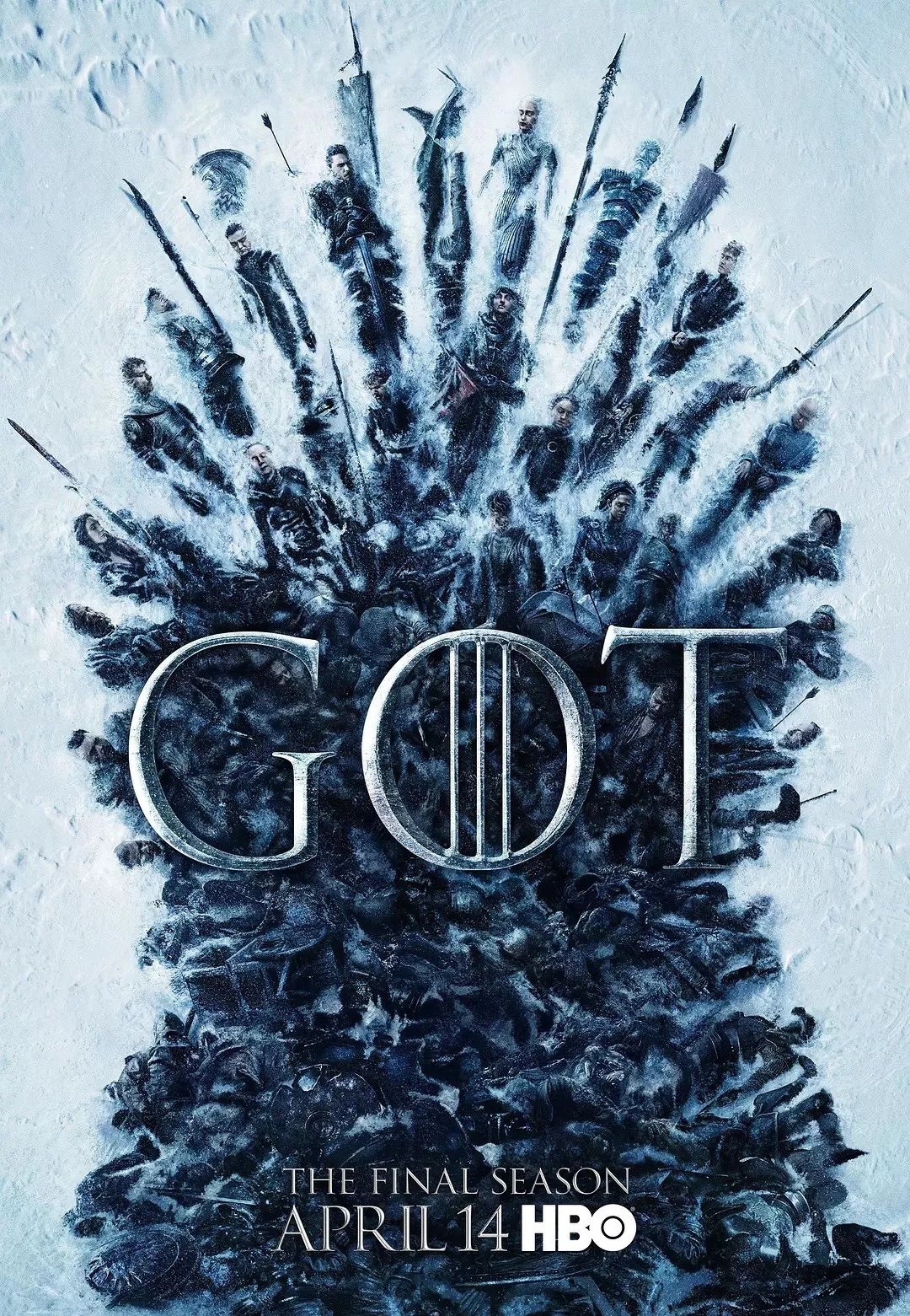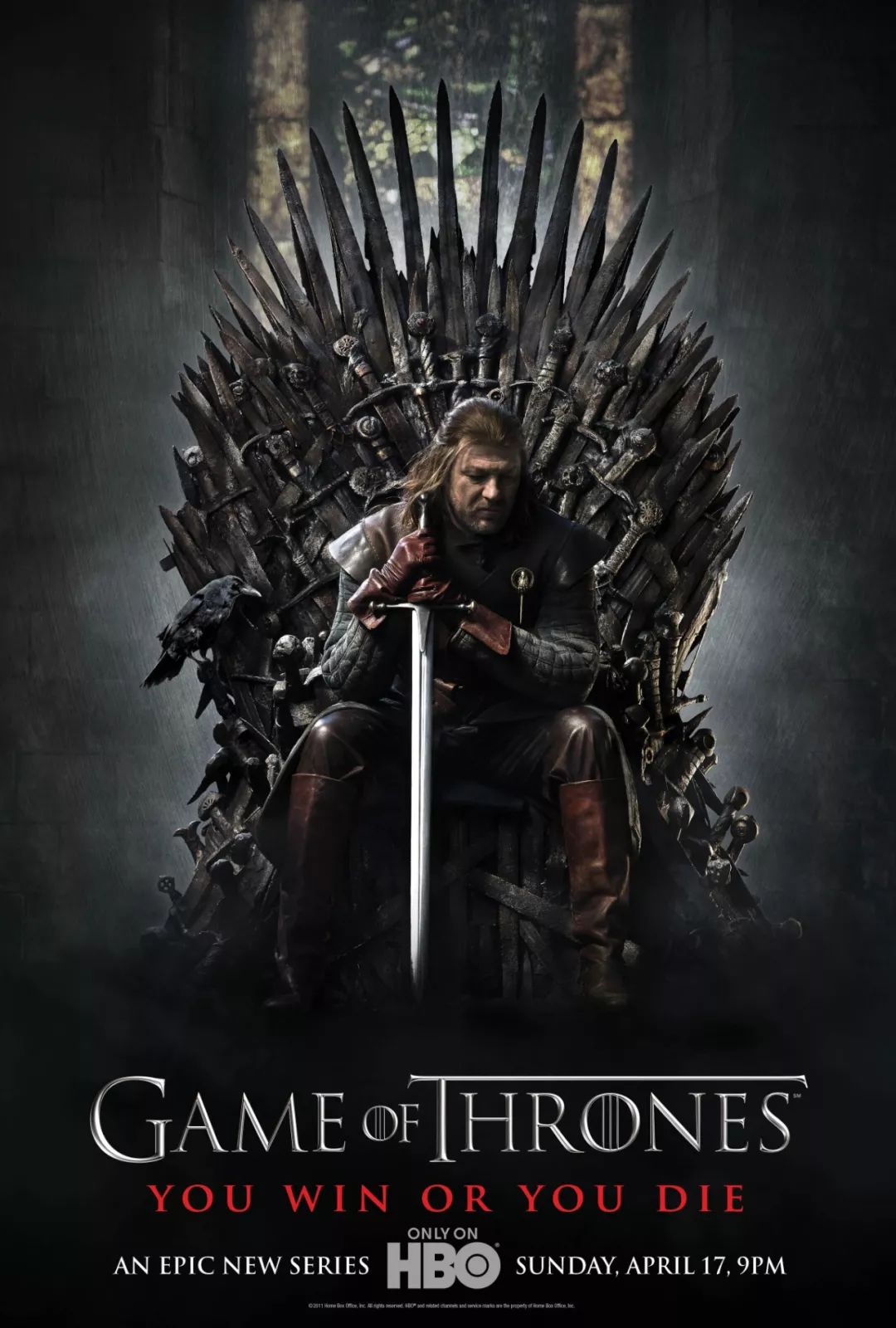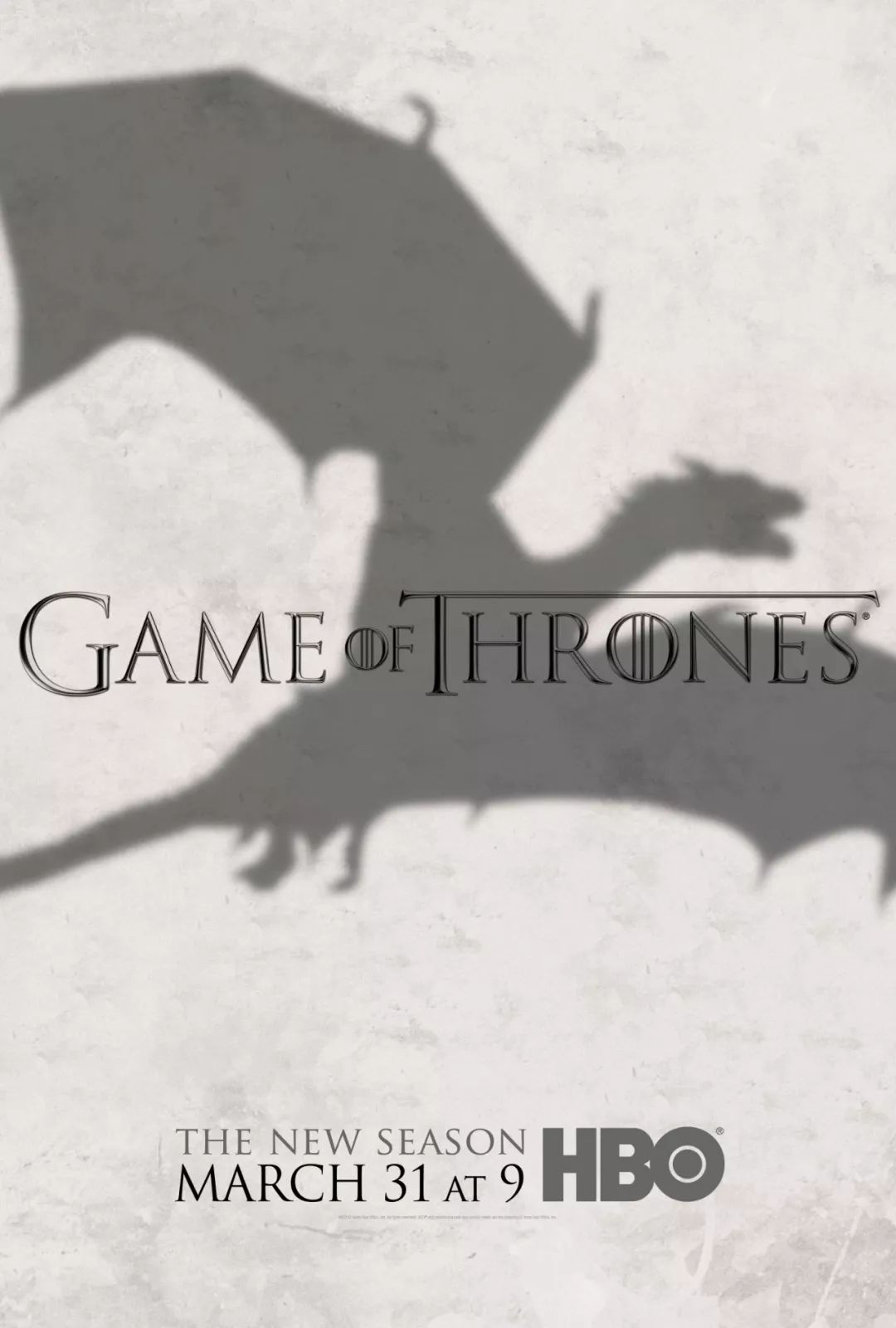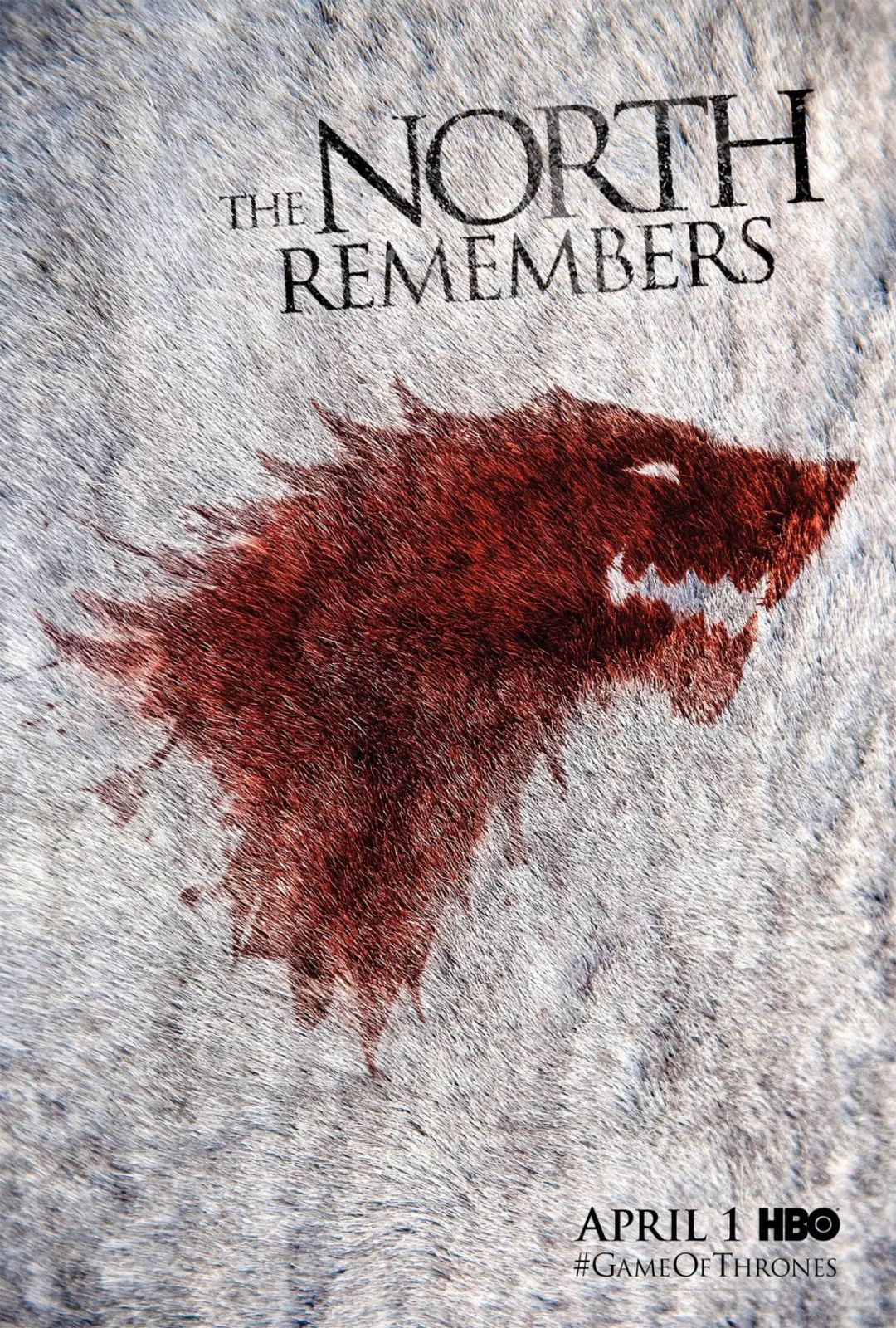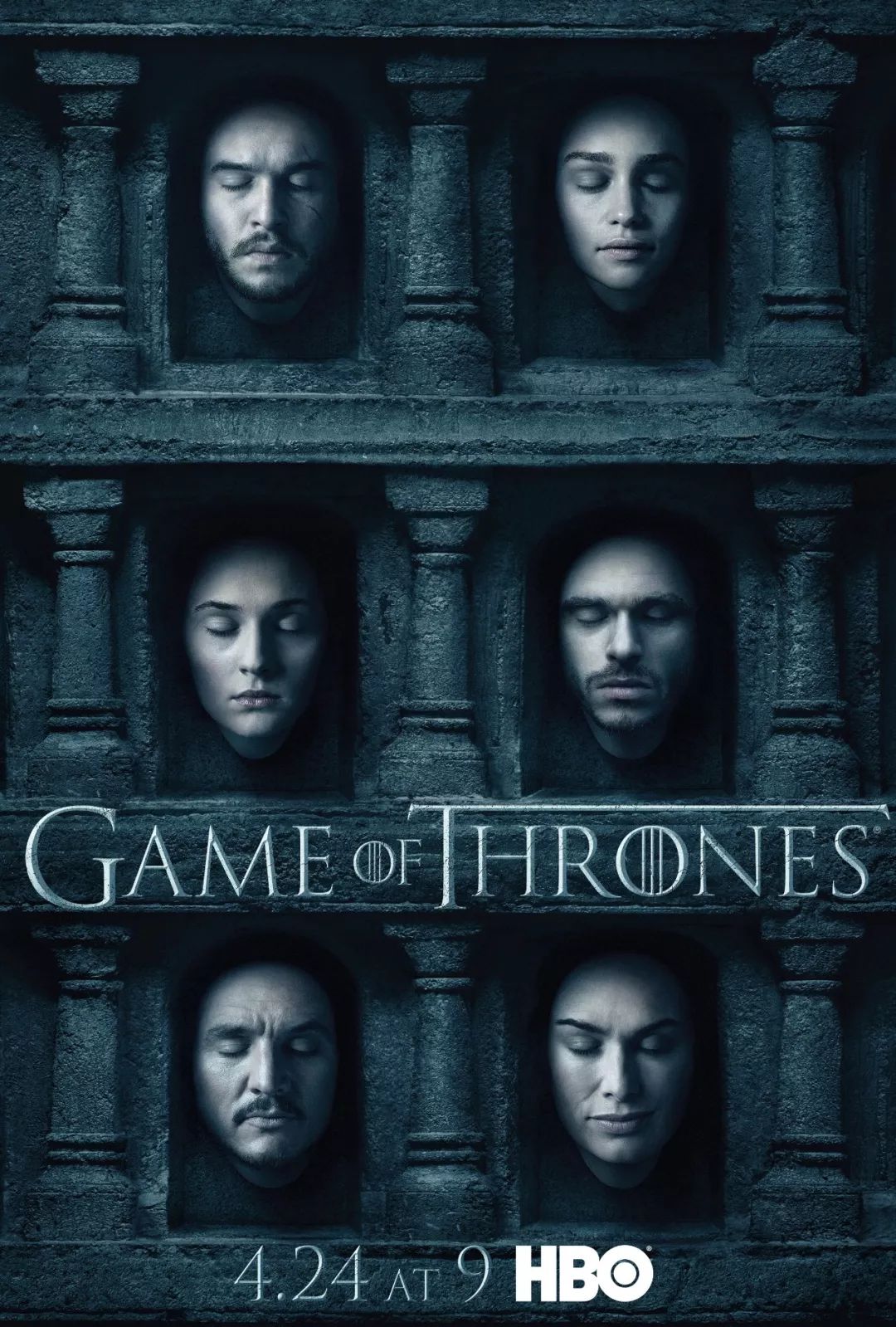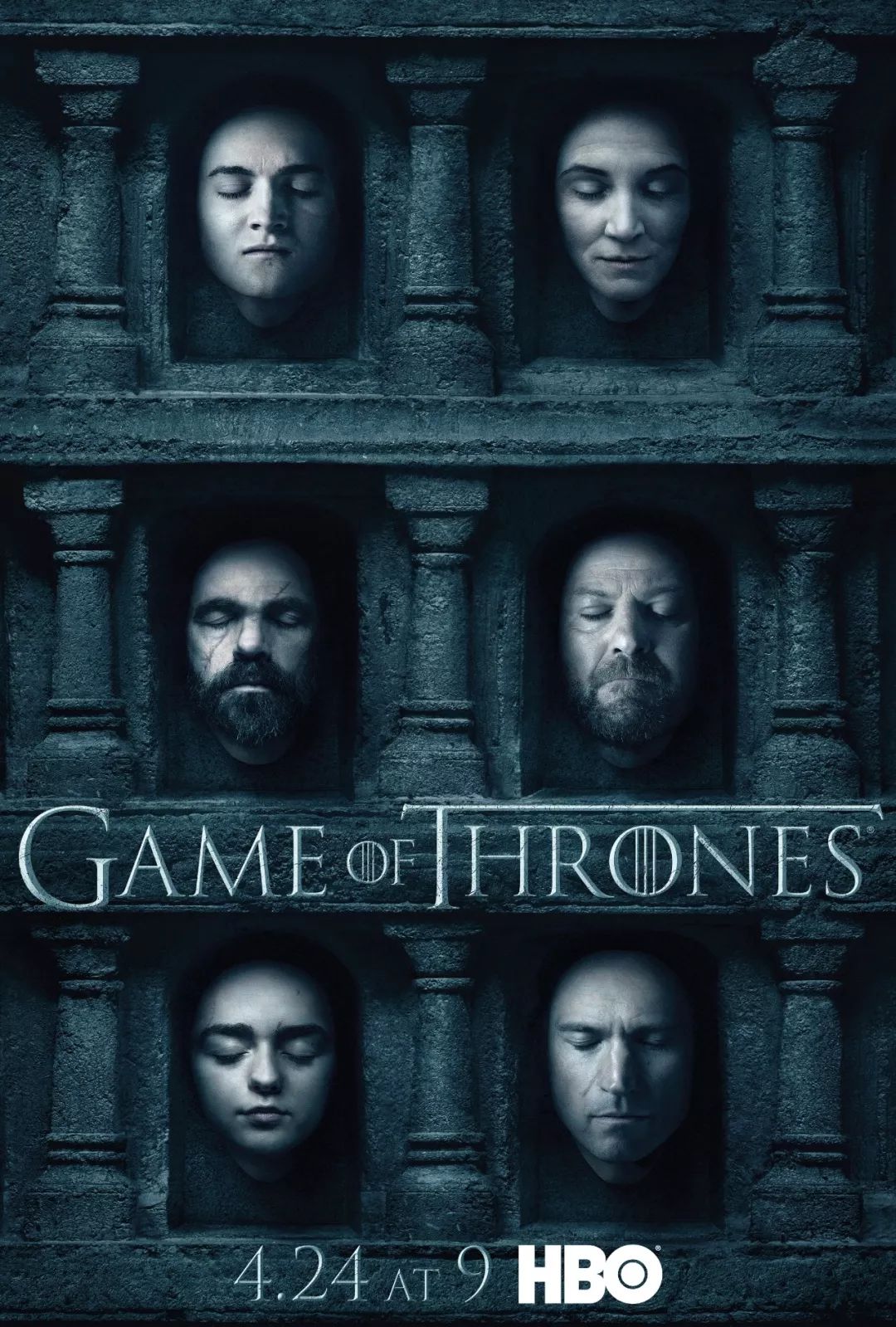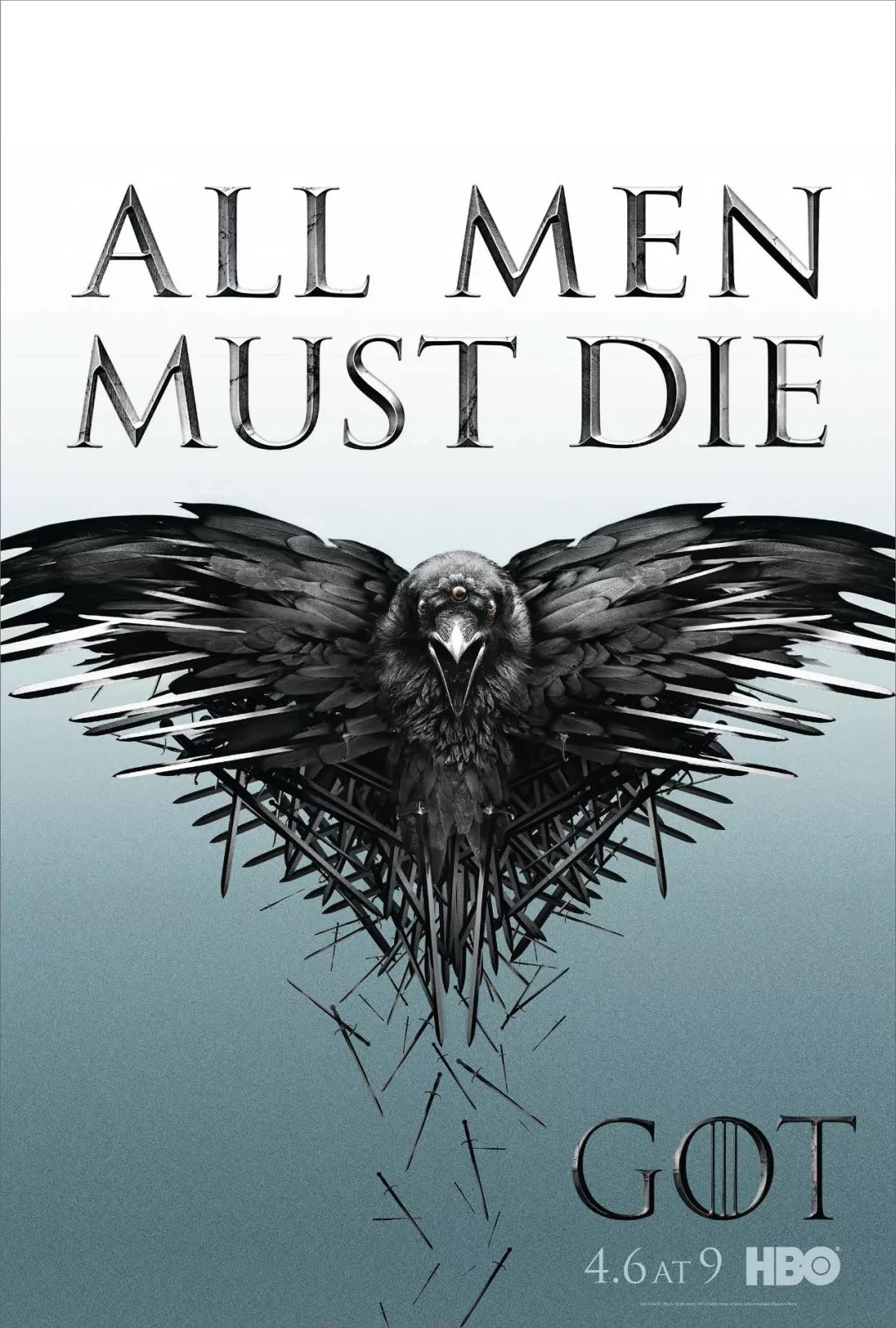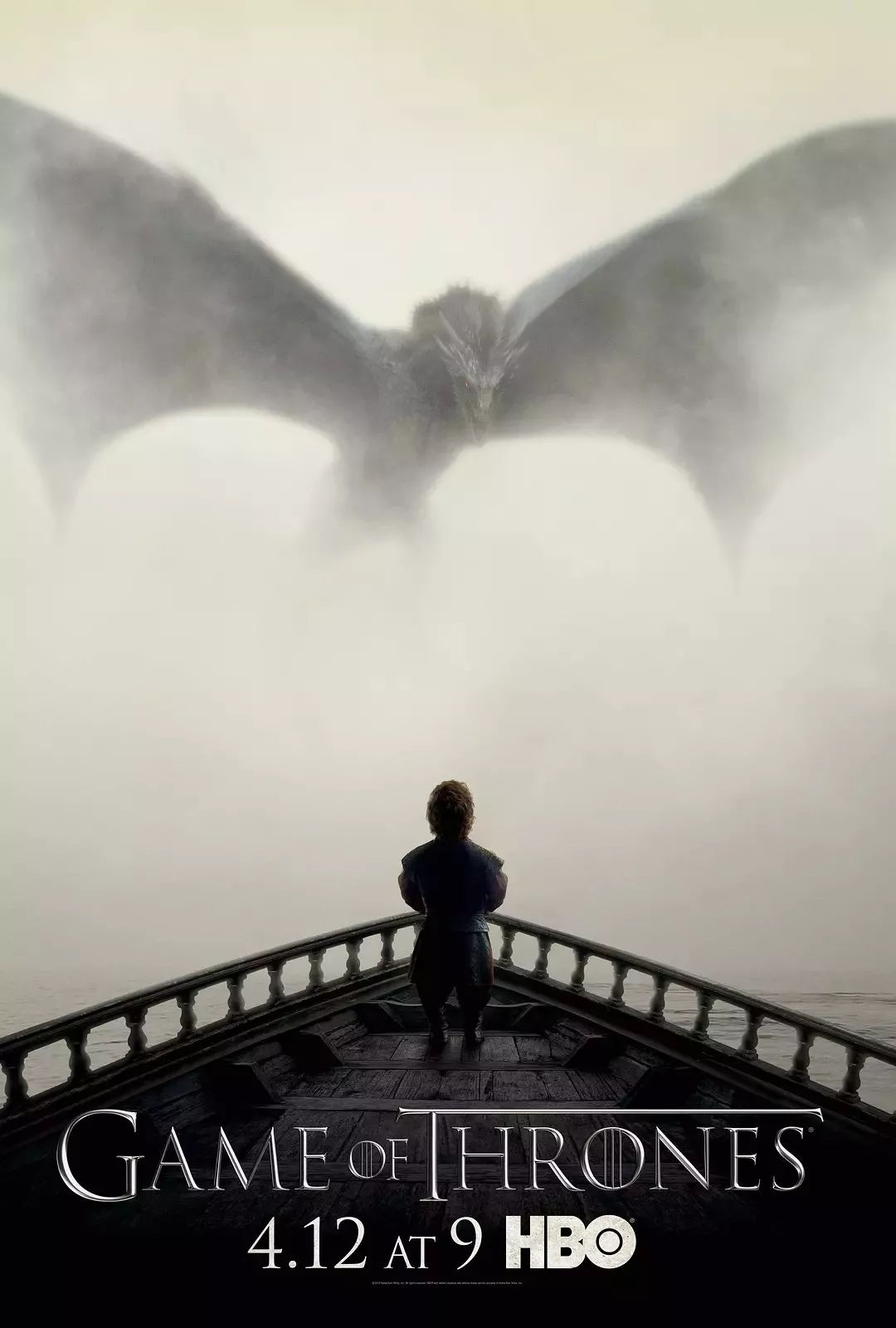
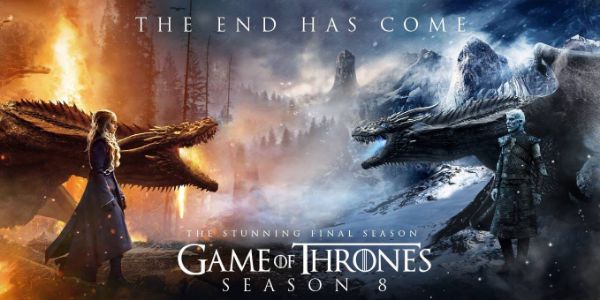
《权力的游戏》才是真正的996
想必大家今天都无心工作,等着追《权利的游戏》第八季吧,作为一个美剧盲的我,也被朋友圈各种“广告”着~
不关注都不行了,可是当我想补课时,却发现进入了一个大坑,这部从2011开播以来的剧,堪称人类的命运史,也就是不断地死亡,不断地权利更替……
看看第八季的海报就知道了~
有点渗人吧,但它的灵感来源却是我们再熟悉不过的了。
很多铁粉试图辨识爱豆的“尸体”,找到故事的结局,不过预告片也可以~
龙妈、夜王、雪诺、小恶魔、二丫、弑君者等21位重要角色霸气亮相,虽然只有短短六集,但投资就高达一个亿(电视剧史上最高),所以即使每周一集,也甘心会员充好(520完结,也是醉了)。
但对于我这种美剧没看过,《权力的游戏》更没听过的小白,有必要三分钟恶补一下。
嗯,还是一头雾水,无奈人物太多,支线太杂,智商有点不够,那就先从海报看起吧~
第一季的海报比较经典,感觉第八季像是跟它呼应一样,只是刚开始挂一个,后面全挂了。
其它角色海报,也是同一个视角,一字排开,但文字排得乱~
最喜欢这张,乌鸦舔血,这才是权利的意境。
第二季很复古,突出了金色字体,但有点《饥饿游戏》的感觉。
预告海报里倒是有几张惊艳之作~
这张真是美出了小龙女的感觉~
第三季有点中规中矩,看不出霸气,只嗅到了一丝诡异~
又是角色海报占了上风,一半是海水。
还有丧尸版阿凡达~
意味深长的棋子~
来到第四季,画风更恐怖,直接告诉你男人都会死。
预告海报也是张张好,多得都放不下,都想抱回家~
终于第五季了,只有一张预告海报,还看不清前方的战况~
倒是粉丝自制海报,有亮点~
越来越惊悚了啊,第六季让我想起了太平间。
都说七年痒一痒,第七季一点都没含糊,主海报就是变异金刚的感觉。
角色海报一水阿凡达~
预告的冰与火之歌,也是里程碑式的好看~
至于今天播出的第八季,除了死尸战术,还有龙龙交战。
还有霸气的家族联合~
不得不提这款破冰海报,完胜官方啊!
回到开头,知道我为啥说它996吗?因为它是2019年开播,又是北京时间上午9点更新,还总共只有6集,不知是巧合还是什么,希望它的出现,能缓解一些对996的焦虑吧,毕竟“凡人皆有一死”。